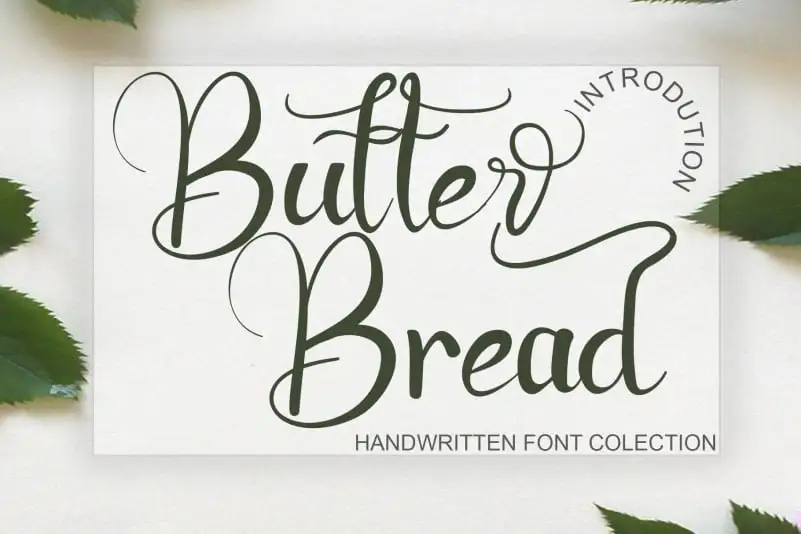
Butter Bread Calligraphy Font – Download Grátis
A Butter Bread Calligraphy Font é uma fonte desenhada à mão com um estilo simples e adaptável. Suas letras são belas e bem equilibradas, fazendo dela uma opção ideal para projetos diversos e criativos. Com seu design versátil e elegante, a fonte se destaca em várias aplicações gráficas. Se você está buscando um estilo único que pode ser aplicado em uma variedade de designs, não hesite em explorar o potencial desta fonte. Ela é perfeita para decorar logos, fazer títulos chamativos ou adicionar um toque especial a qualquer projeto gráfico. Não importa qual seja seu próximo design – a Butter Bread Calligraphy Font certamente merece uma chance.